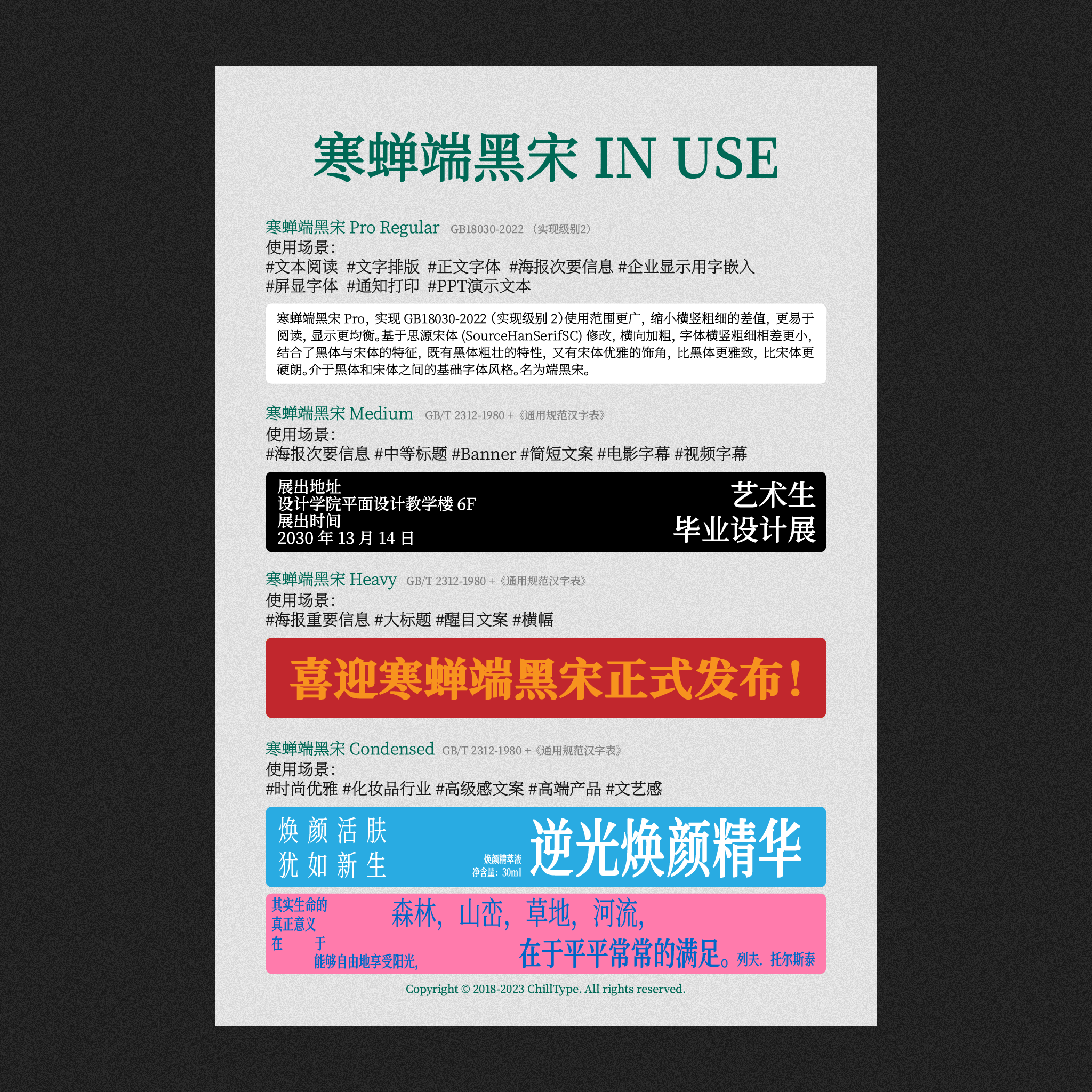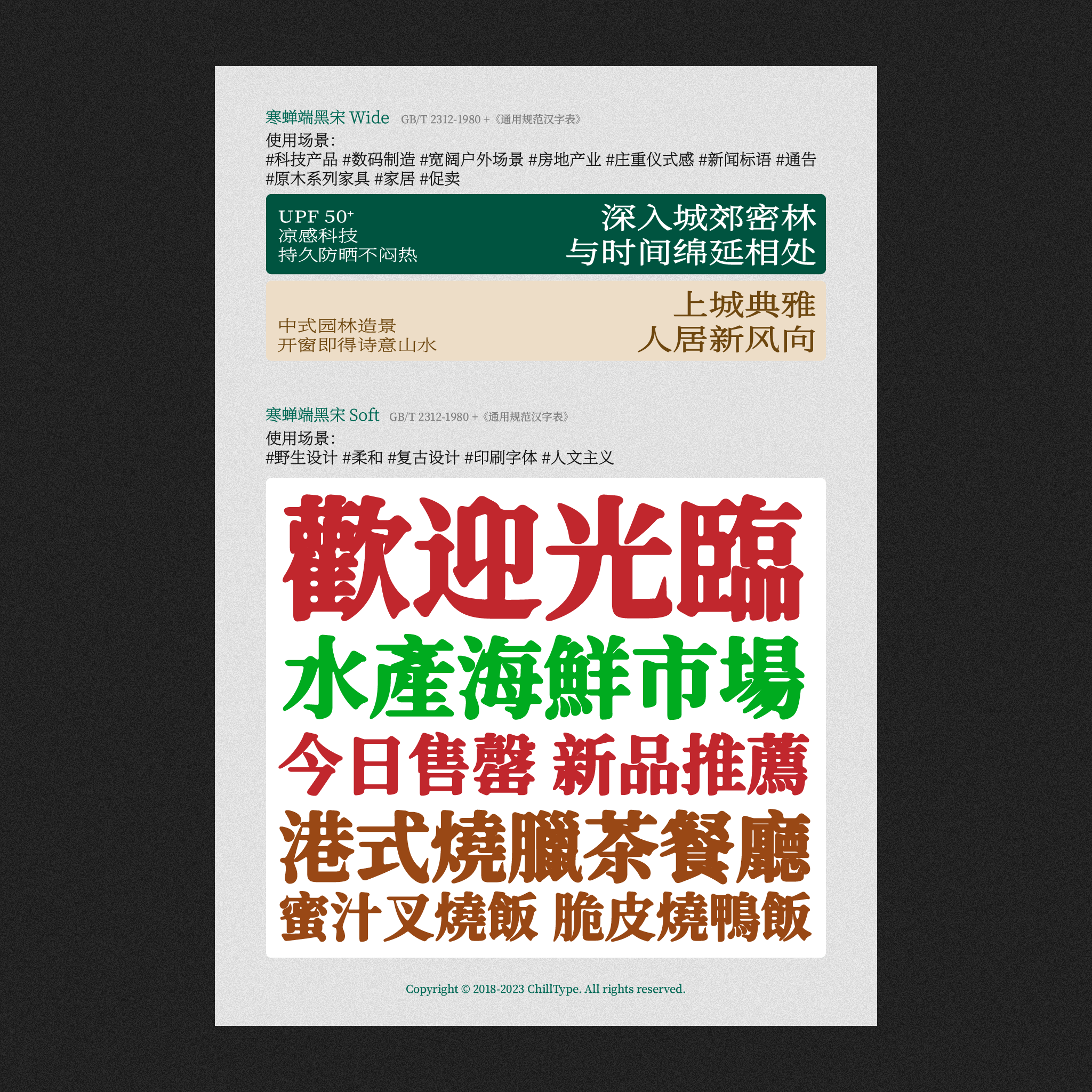
寒蝉端黑宋这款字体,是以思源宋体(Source Han Serif SC)为基础进行深度定制与改良而成的。其核心设计思路在于对字形结构进行横向的适度加粗处理,使得笔画的横向与纵向粗细对比度进一步缩小,达到了更为均衡的视觉效果。这一调整巧妙地融合了黑体与宋体两大字体家族的经典特征:它既汲取了黑体笔画均匀、结构粗壮、现代感强烈的基因,赋予了字体扎实稳重的基础骨架;同时,它又保留了宋体传统而精致的装饰性衬线(即“饰角”),为整体字形注入了一份典雅与书卷气。
因此,寒蝉端黑宋呈现出一种独特的双重性格:它比纯黑体显得更为雅致、细腻,削弱了部分冰冷感与工业感;而相较于传统宋体,它又显得更加硬朗、饱满,在保持优雅风度的同时增强了力量感与可读性。这种特质使其恰好定位在黑体与宋体之间的广阔光谱之上,形成了一种兼具传统韵味与现代气质的“基础字体风格”,既适用于需要稳重感的标题排版,也能胜任要求清晰易读的正文环境,为设计者提供了一种平衡、通用且富有层次感的新选择。其命名“端黑宋”,正是对这种端庄、稳重,又融合了黑宋精髓的字体特性的精准概括。